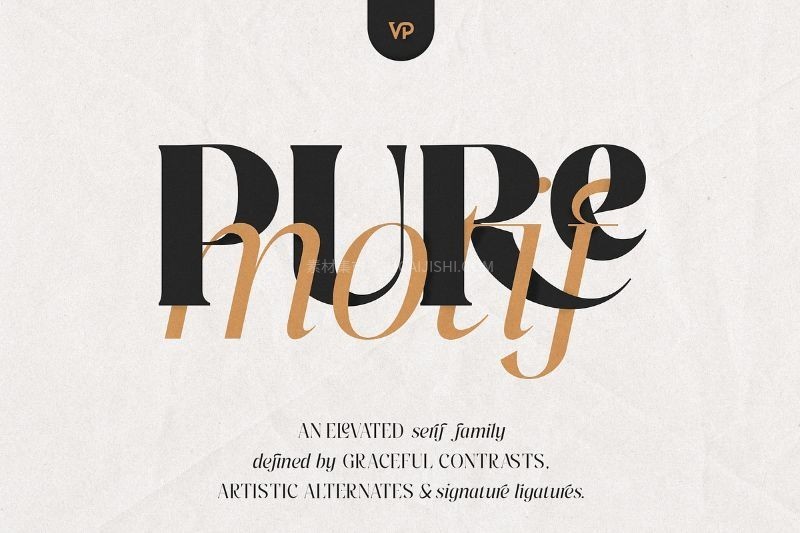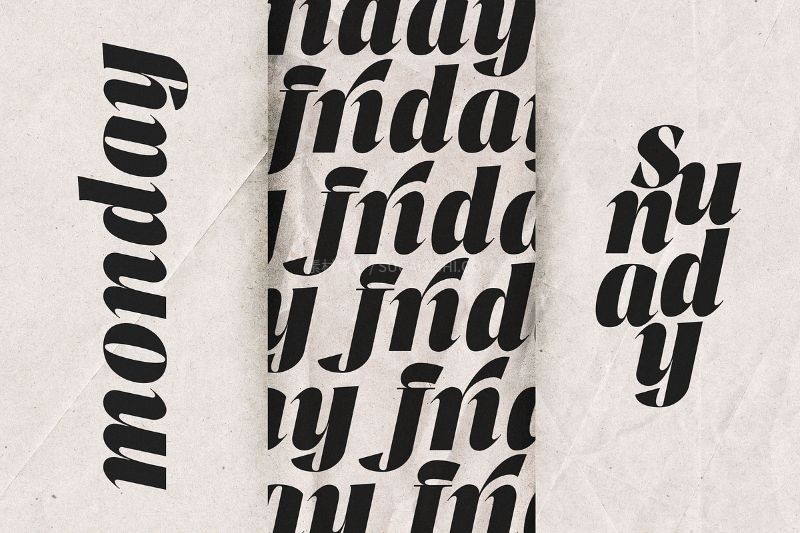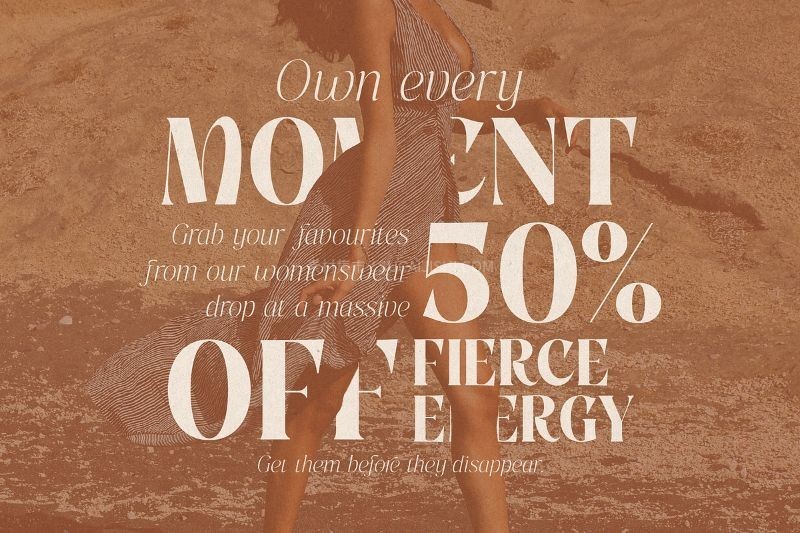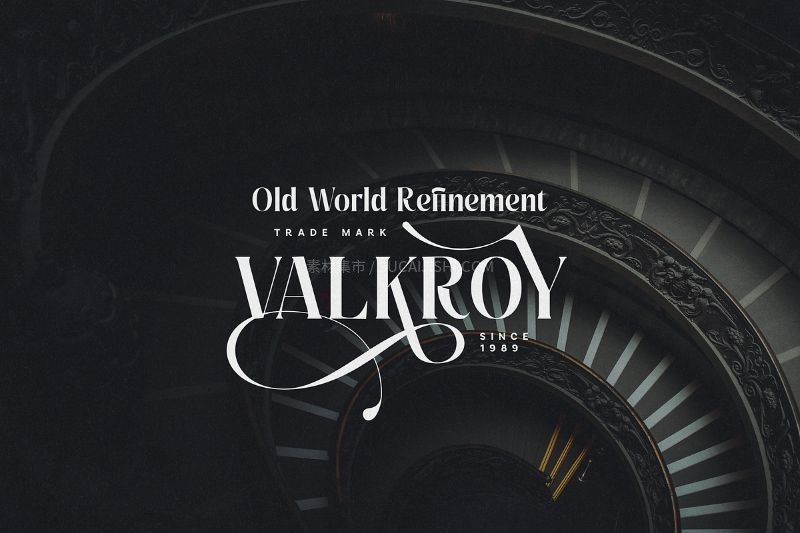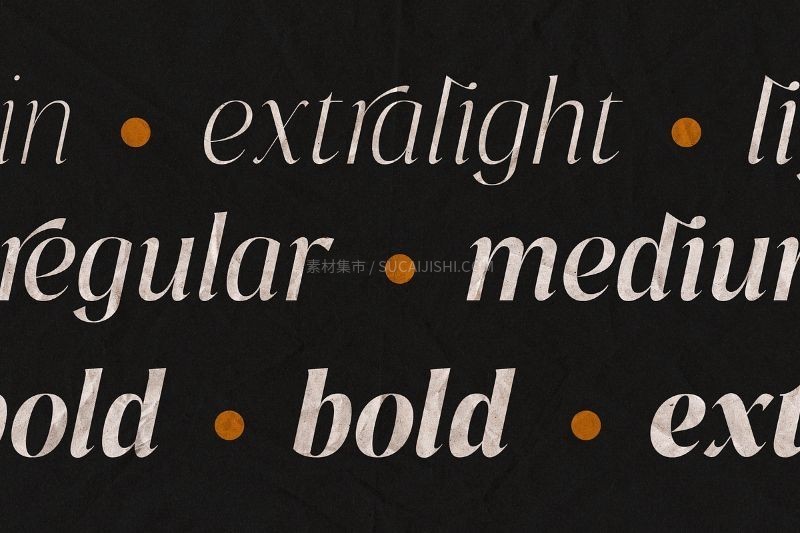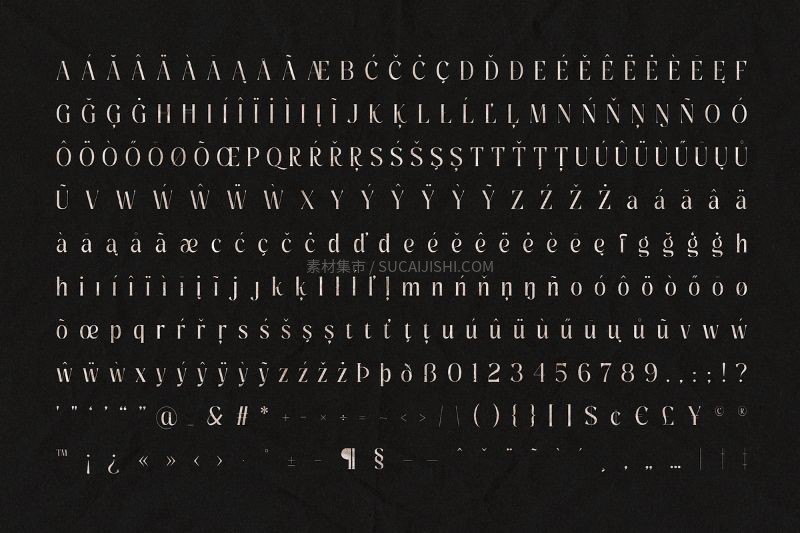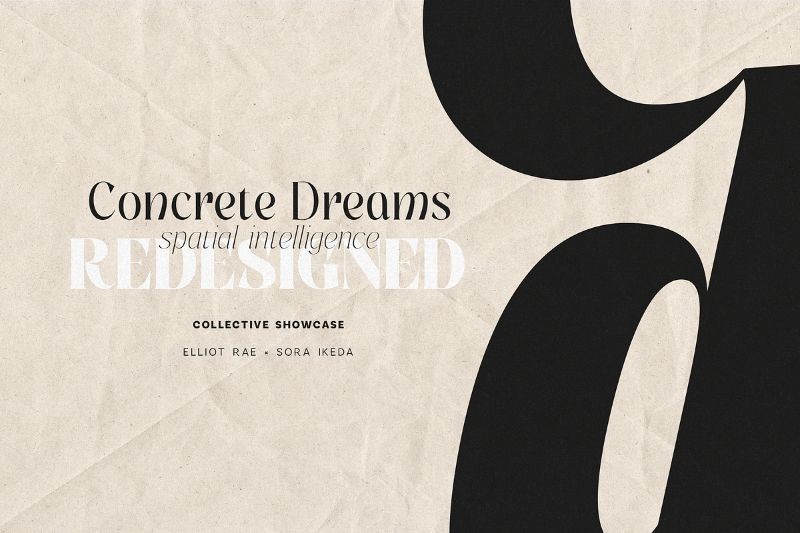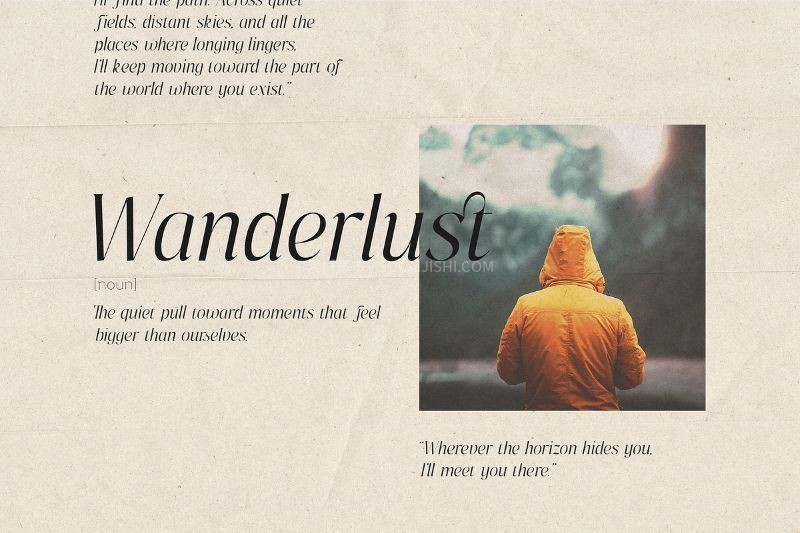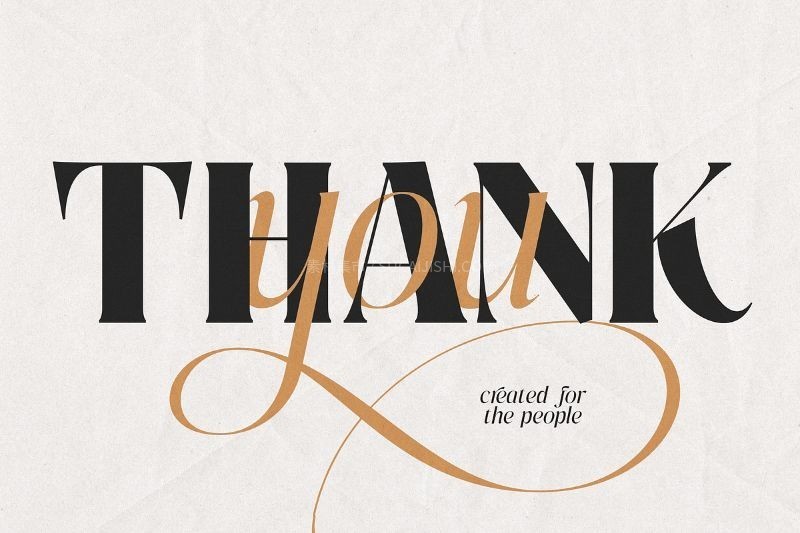
Pure Motif 高雅英文衬线字体
Pure Motif 是一款融合了经典工艺与当代艺术审美的精致衬线字体。该字体家族包含从细体到黑体共9种字重,配备富有表现力的真斜体、可变样式及多种风格备选方案。其标志性的连字设计能打造出流畅且极具个性化的文字商标。Pure Motif 拥有优雅的对比度、流畅的曲线和雕塑般的笔画末端,支持超过87种拉丁语系语言,经过专业的字距与间距调整,完美适配跨印刷与数字平台的各种高品质设计需求。
Pure Motif 高雅英文衬线字体
适用高端品牌视觉识别(VI)、时尚编辑排版、奢华产品包装、Logo设计、生活方式类海报、书籍封面、婚礼请柬及网页标题设计